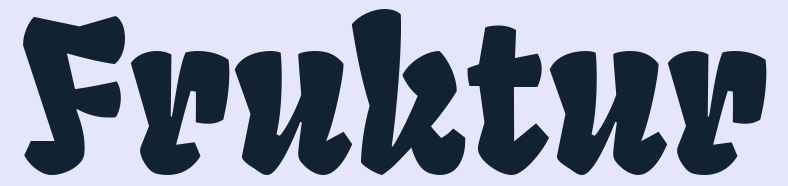
Suche neue gebrochene Schriften
Hmm, irgendwie "Schaftsiefel-Arial"
Hier würde ich nahezu den gleichen Kommentar, wie ihn Ralf im Schwester-Pfad gegeben hat schreiben. Irgendwie auch aufgesetzt, und die Winkel und Strichstärken-Variation nicht aus den Linienzügen einer Breitfeder abgeleitet, was zu Formen führt, bei denen geine Ursache zu sehen ist.
… und die Winkel und Strichstärken-Variation nicht aus den Linienzügen einer Breitfeder abgeleitet …
Zumindest ein frischer Wind, im Gegensatz zu den vielen geklonten Gebrochenen.
Wenn etwas Neues entstehen soll, ist es auch nötig, neue Wege zu beschreiten.
Ist es zwingend, dass eine gebrochene Schrift dem Breitfeder-Duktus entspricht?
Ob diese Schrift den Geschmack trifft, steht auf einem anderen Blatt.
Wenn dann aber die Definition von "Gebrochener Schrift" nur noch bedeutet, das die Schrift Exken hat, dann sind auch das gebrochene Schriften:
Wenn dann aber die Definition von "Gebrochener Schrift" nur noch bedeutet, das die Schrift Exken hat …
das habe ich weder geschrieben noch gemeint. Auch nicht die von dir gezeigten Schriften.
Vielmehr meinte ich, dass, um etwas Neues zu „erfinden“, tradierte Arbeitsmethoden auch ignoriert werden können.
Das heißt, man kann den Bogen ruhig einmal überspannen. Und 2 x 2 kann auch fünf sein.
Bei den ersten Druckschriften hatte man noch den Schreibduktus verfolgt, eben um an dem alten Stil der Schriften nicht viel zu verändern.
Das Streben Neues zu erfinden hat aber im Laufe der Jahrhunderte bei manchen Schriften kaum noch etwas davon übriggelassen.
Aus der Antiqua wurde die Grotesk entwickelt. Vom Duktus des Federzugs ist nichts mehr übriggeblieben. Die handgeschriebene Form ist oftmals einer konstruierten Form gewichen. (Wurde hier schon diskutiert)
Warum sollte dies nicht auch auf die Gebrochenen zutreffen?
Als Beispiel einer Gebrochenen ohne dem typischen Breitfedernzug siehe bitte hier: